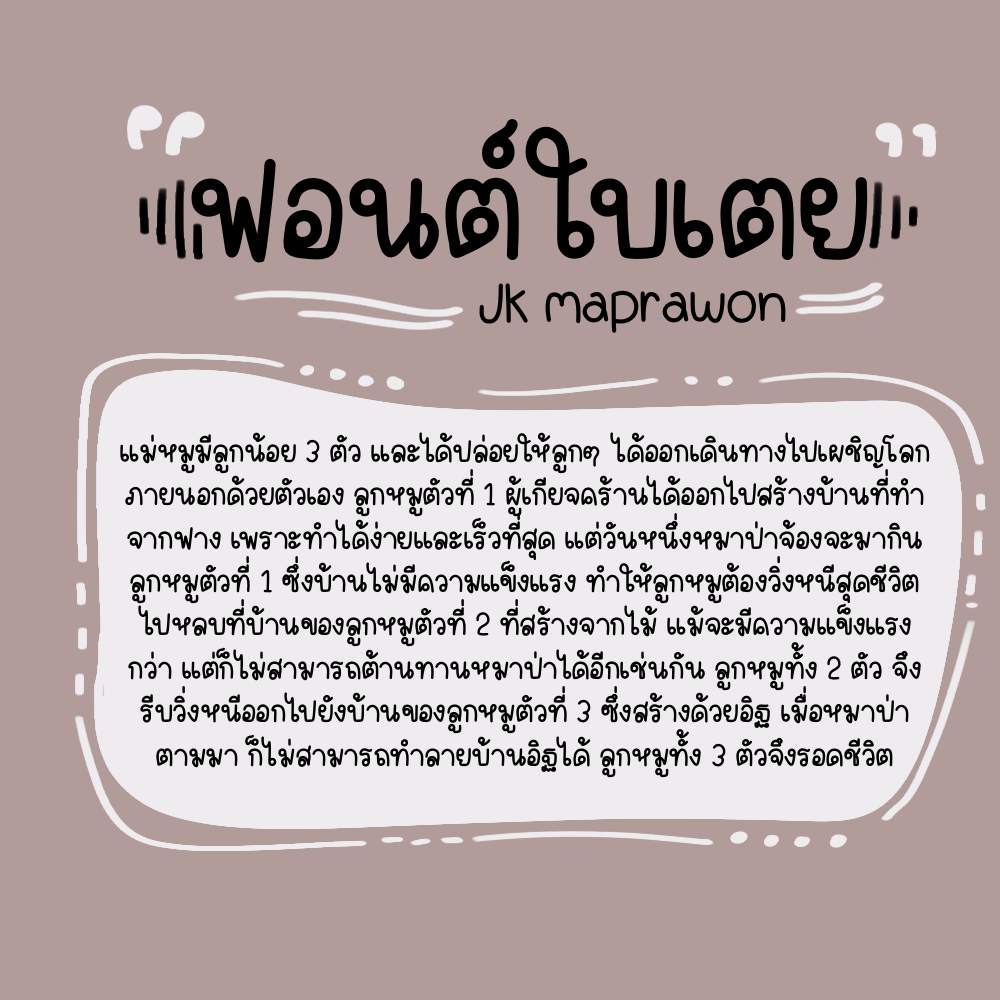
ใบเตย (JK baituiy)
ฟอนต์ ใบเตย (JK baituiy) ฟอนต์ที่มีเอกลักษณ์ ใช้ทำงานสไตล์น่ารักๆ จดโน้ต หรือจะทำแฟลชการ์ดก็ดูดี แจกฟรีไปเลยเวอร์ชันทดลอง : แบบปกติ 1 น้ำหนัก ใช้ได้เฉพาะแบบส่วนตัว เช่น ใช้ในการศึกษา ใช้จด ใช้ตกแต่งสมุดโน้ตตัวเอง